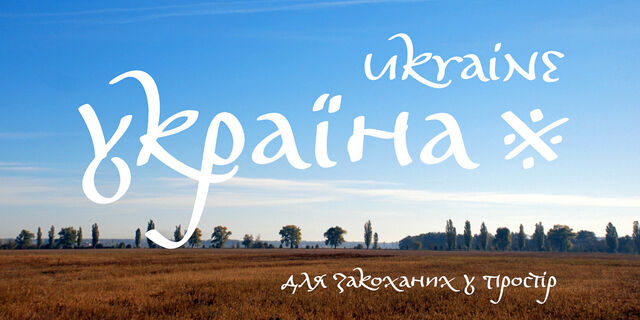
Гайдамака — бескомпромиссный шрифт без кернинга, без больших букв, без исторических прототипов, но, безусловно, с характером! Созданный в далеком 2007-м году, этот скрипт, названный в честь гайдамаков, украинских партизан прошлых веков, становится в строки живо и нагло. Шрифт экспонировался на легендарном фестивале «Свято Кирилиці» в Харькове, немного побыл частью туристического логотипа Украины. Содержит знаки европейской кириллицы, неакцентированную латиницу, цифры и немного дополнительных символов. Деньги от продажи этого шрифта идут на благотворительные нужды, подробности читайте здесь: https://www.facebook.com/groups/151717195372009/posts/1008076373069416/ Дизайн шрифта — Андрей Шевченко. Презентационные картинки — Богдан Гдаль.